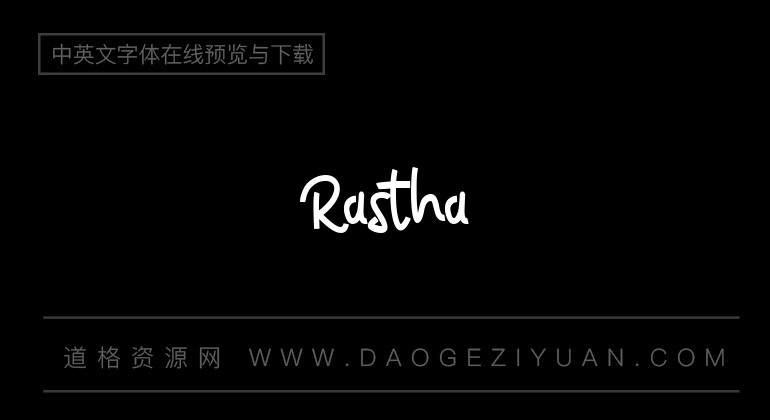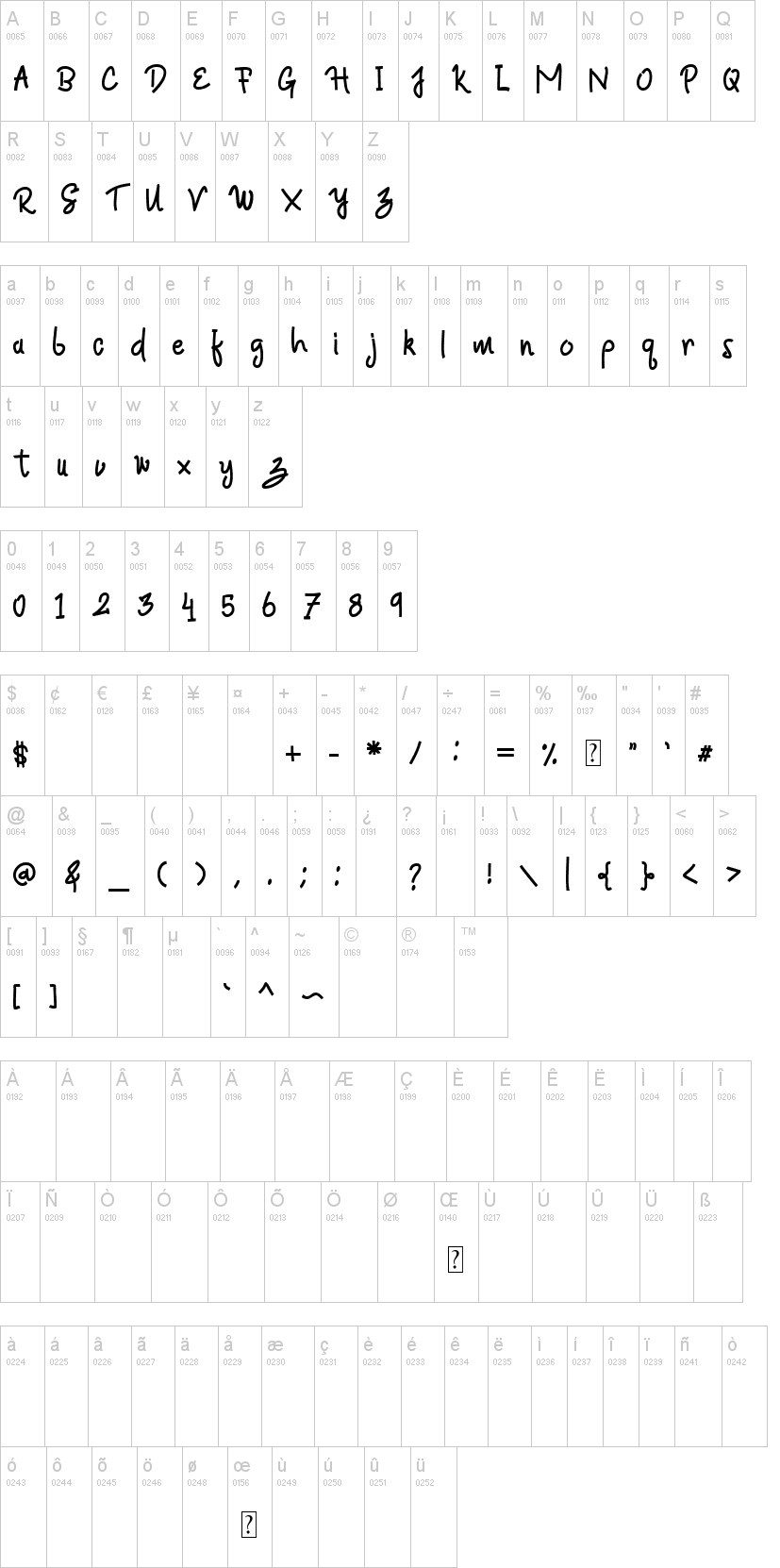
Rastha
? Rastha 字体是一种印度的传统字体,又称为拉斯达字体。它是一种结构紧凑的斜体字体,特别适合用于小型文本和图形。它的字形精细,拥有极具美感的笔画,比较适合用于手绘图形设计。Rastha 字体的字形比较细,可以更好地传达文字的意义,这也是它受欢迎的原因之一。
Rastha是一款非常不错的手写艺术字体,具有很好的视觉感,适合于文化类的宣传设计、商业类品牌的广告和产品包装设计以及个性化文字排版等较多场景。
Rastha字符映射图